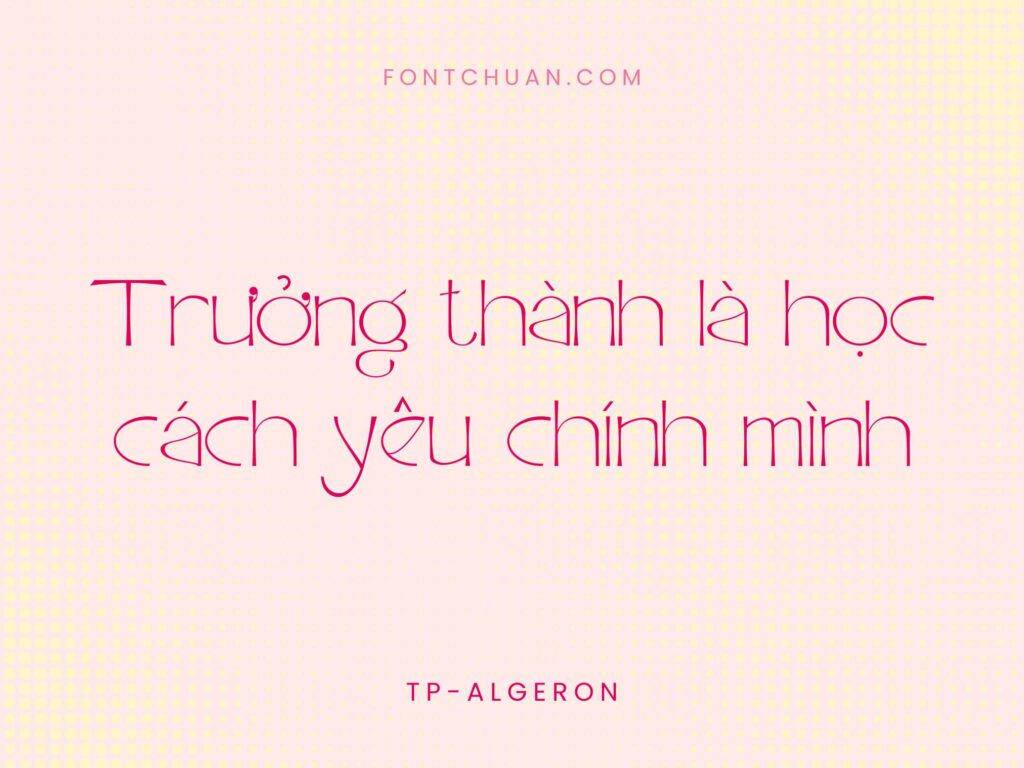
Font TP Algeron Việt Hóa
Algeron là một font chữ serif mảnh mai với cảm giác dân tộc và nét hiện đại, được thiết kế bởi Jolicia Type. Font này cung cấp nhiều lựa chọn thay thế, cho phép bạn kết hợp theo phong cách của riêng mình. Font đã được Việt hóa để hỗ trợ tiếng Việt bởi Tuỳn Pucca, đồng thời hỗ trợ nhiều ngôn ngữ khác, giúp mở rộng phạm vi sử dụng trên toàn cầu. Font này được sưu tầm và chia sẻ bởi thành viên của Font Chuẩn, đáp ứng nhu cầu của người dùng và ứng dụng thực tế vào các dự án thiết kế.
Đặc điểm thiết kế của Algeron bao gồm các đường nét mảnh mai và tinh tế, tạo cảm giác thanh lịch và hiện đại. Font này phù hợp cho các ứng dụng như tiêu đề, logo, thiết kế thiệp cưới và các dự án sáng tạo khác. Các ngành nghề phù hợp bao gồm quảng cáo, nghệ thuật và thiết kế đồ họa.